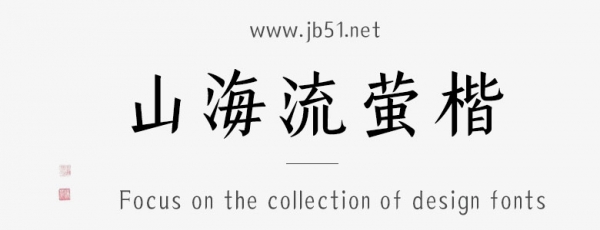
山海流螢楷家族是由山海字庫(kù)出品的字體,這款字體擁有六款字重,端正大氣,具有很好的視覺(jué)感,適合應(yīng)用于藝術(shù)設(shè)計(jì)、平面宣傳設(shè)計(jì)、網(wǎng)頁(yè)設(shè)計(jì),書(shū)法字帖等領(lǐng)域,需要的朋友可以前來(lái)本站下載。
山海流螢楷,由山海字體社出品。本字體為簡(jiǎn)繁字庫(kù),采用Adobe-GB1-5編碼,包含常用簡(jiǎn)體(GB2312-80)6763個(gè),繁體(GBK)2406個(gè),共計(jì)9169個(gè)漢字;以及
ASCII常用西文200+。6個(gè)字重-45-Light55-Normal65-Regular 75-Medium 85-Bold 95-Heavy